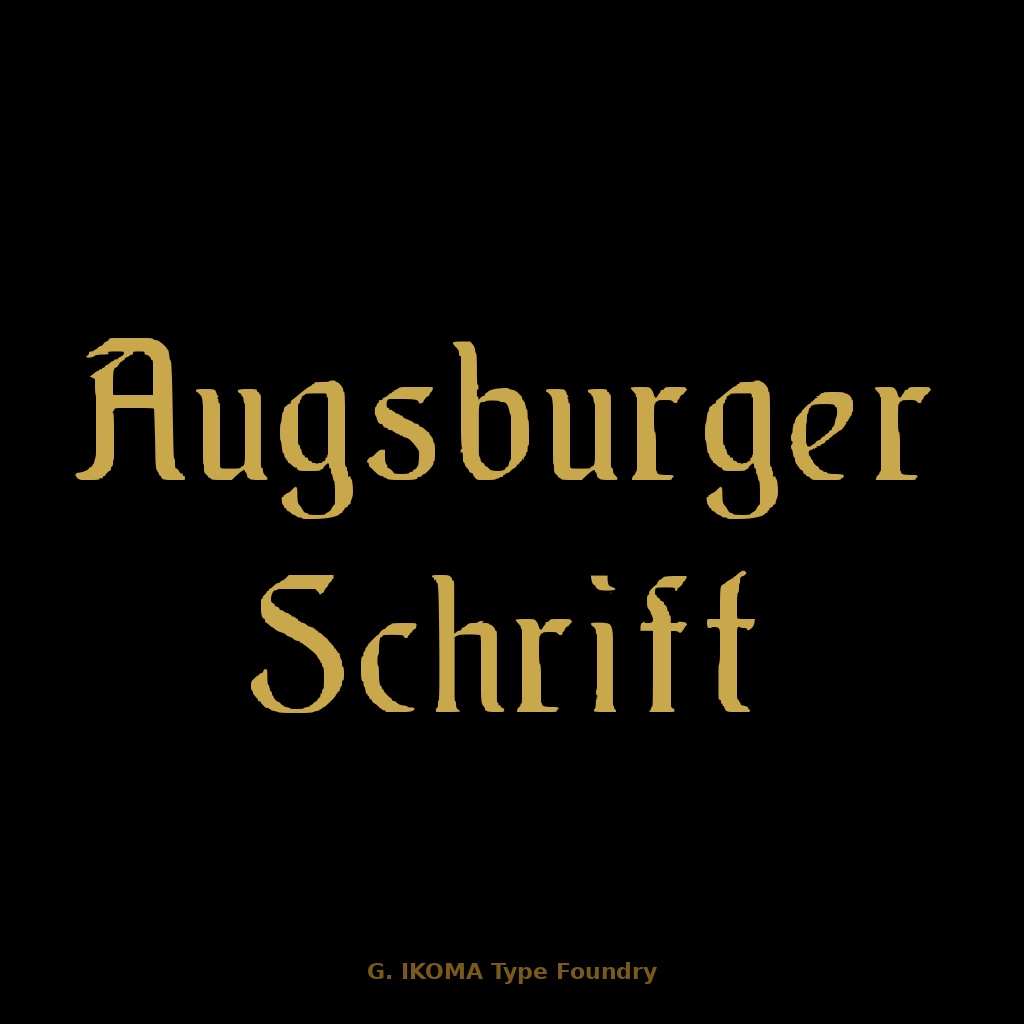
Augsburger Schrift — 19世紀欧州印刷資料復元フォント / Historical Revival Typeface [Jugendstil / Semi-Uncial]
a━━━━━━━━━━━━━━━━━━━━━━━━━ 【フォントについて】 ━━━━━━━━━━━━━━━━━━━━━━━━━ Augsburger Schrift Extended は、19世紀末ドイツの活字見本帳を原典に、手作業でトレース・デジタル化した復元フォントです。 本作は、H. Berthold(Berlin)および Bauer & Co.(Stuttgart)による Jugendstil 様式の書体をもとに再構成したものです。 セミ・アンシャル(半角書体)の流れを汲む独特の筆致と、中世ドイツ書体の力強さを併せ持つ、19世紀末〜20世紀初頭の欧州印刷文化を代表する書体です。 原典:H. Berthold, Berlin & Bauer & Co., Stuttgart 活字見本帳(パブリックドメイン) 様式:Jugendstil / Semi-Uncial(ユーゲントシュティル/セミ・アンシャル) 収録グリフ:62文字(A-Z・a-z・0-9)+記号類32 欠落グリフ:なし 制作:株式会社生駒時計店 / G. IKOMA, LTD.(1870年創業) ━━━━━━━━━━━━━━━━━━━━━━━━━ 【収録内容】 ━━━━━━━━━━━━━━━━━━━━━━━━━ ・I_Augsburger_Schrift_Extended.ttf ・LICENSE.txt(日英) ━━━━━━━━━━━━━━━━━━━━━━━━━ 【ライセンス】 ━━━━━━━━━━━━━━━━━━━━━━━━━ 個人・商用利用可。印刷物・ロゴ・画像・動画サムネイル等に使用可能。 禁止:再配布・再販売・Webフォント設置・アプリ埋め込み・AI学習利用。 詳細は同梱 LICENSE.txt 参照。 ━━━━━━━━━━━━━━━━━━━━━━━━━ 【原典資料について】 ━━━━━━━━━━━━━━━━━━━━━━━━━ G. IKOMA Archive: https://g-ikoma-archive.netlify.app/ BOOTH: https://g-ikoma.booth.pm/